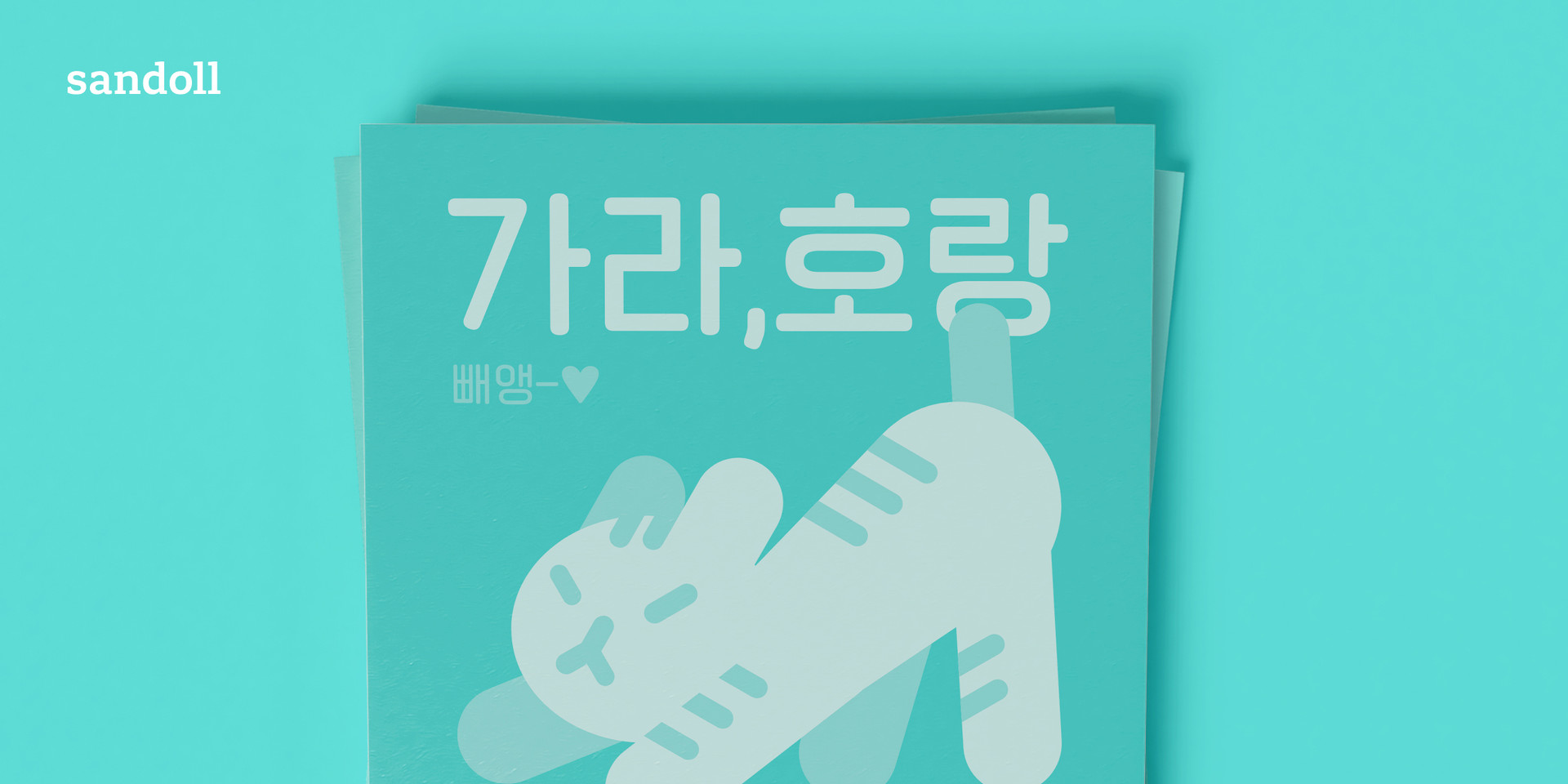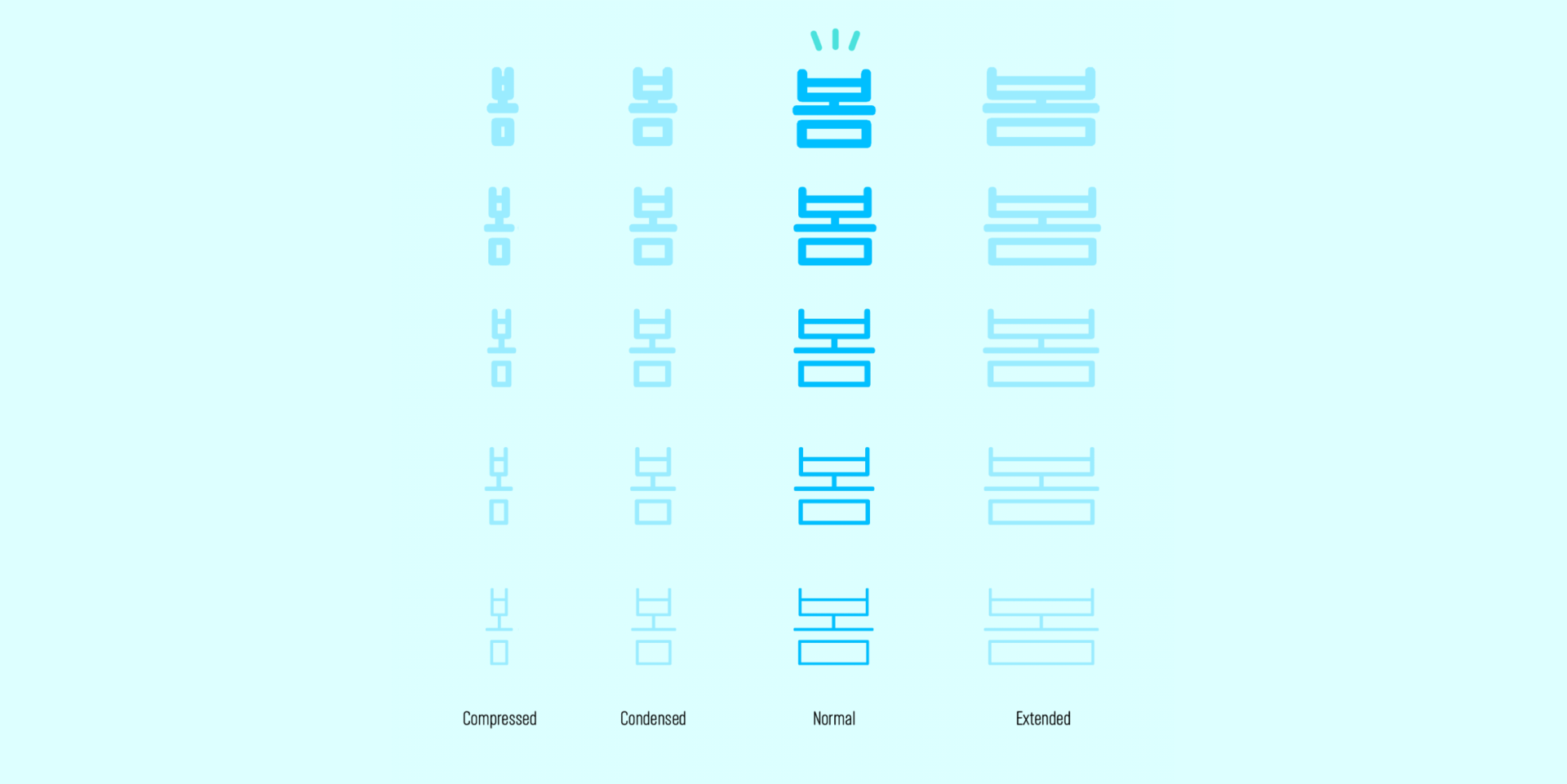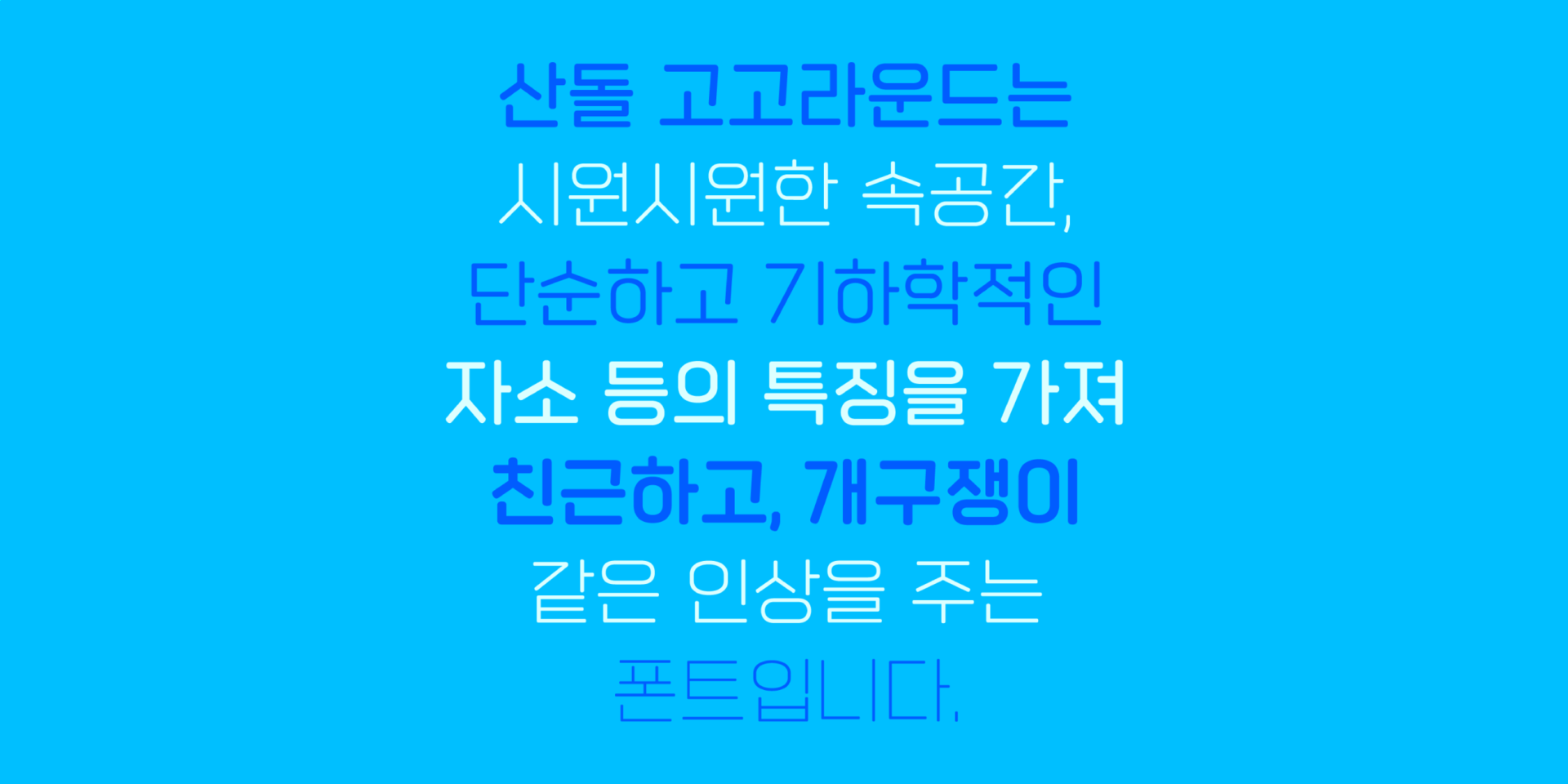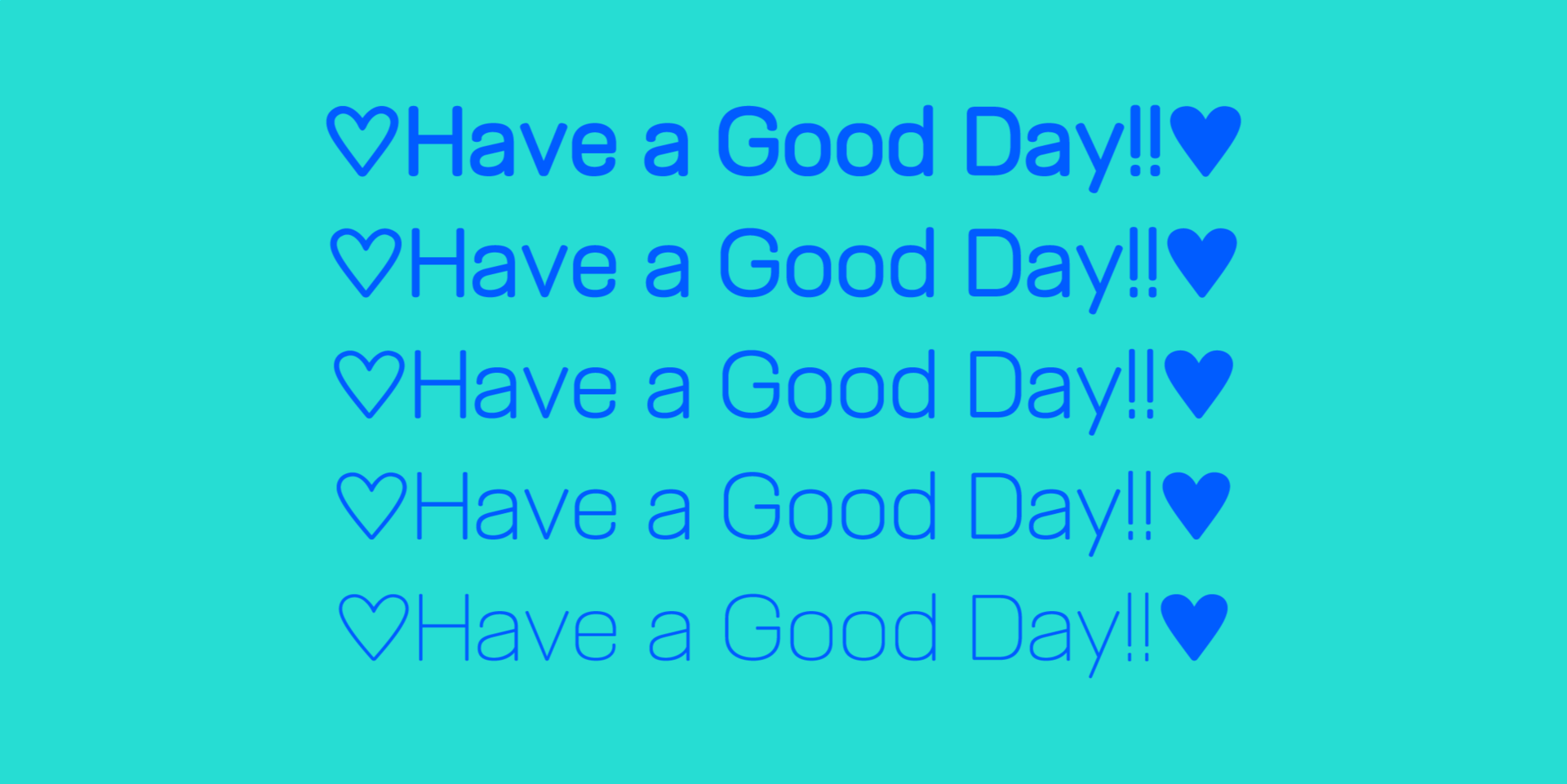
Sandoll 고고라운드
산돌 고고 패밀리의 두 번째 시리즈, 산돌 고고라운드를 소개합니다.
산돌 고고는 시원시원한 속공간, 단순하고 기하학적인 자소 등의 특징을 가져 친근하고 개구쟁이 같은 인상을 주는 폰트입니다. 산돌 고고라운드는 산돌 고고 패밀리의 라운드 버전이면서 동시에 2020년 6월에 출시한 Sandoll gogo Round condensed보다 폭이 넓은 Normal 버전이기도 합니다.
고고라운드는 Thin, Light, Regular, Semibold, Bold의 총 5가지의 굵기 패밀리를 가지고 있고 획이 얇아짐에 따라 달라지는 속공간과 획의 마감을 신경 써서 작업했습니다. Sandoll Gogo Round Condensed와도 함께 쓸 수 있도록 설계하여 같은 패밀리끼리 비슷한 룩을 유지하도록 힘썼습니다. 한글은 11,172자 스펙으로 구성하여 사용성을 더욱 높였습니다. 친근하고 개구쟁이 같은 인상을 가지고 있고 5개의 웨이트를 갖췄기 때문에 포스터의 제목, 각종 인쇄물, 영상의 다양한 자막(상황 자막, 줄 자막 등)에 사용하기 좋습니다.